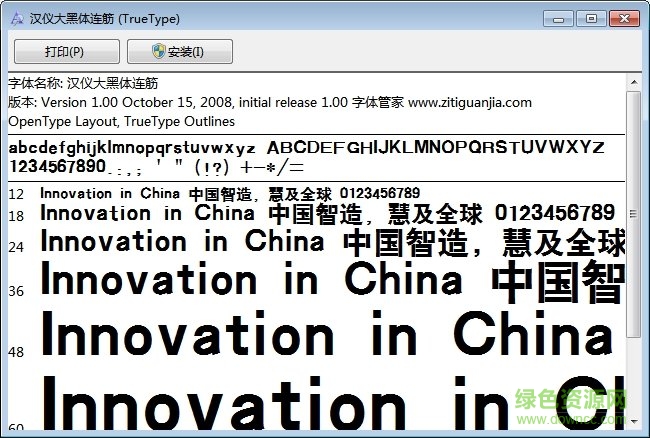
漢儀大黑體連筋字體是一款造型大氣恢弘、字跡清晰正直,給人十分醒目嚴(yán)肅的藝術(shù)體驗(yàn),用于正規(guī)條文、重要事情公告等標(biāo)準(zhǔn)文件上使用效果特別好,歡迎大家來綠色資源網(wǎng)下載收藏!
漢儀大黑連筋字體字形方正,筆畫橫平豎,直角分明,結(jié)構(gòu)嚴(yán)謹(jǐn),整齊均勻,整體風(fēng)格十分穩(wěn)重,常用作印刷中穩(wěn)重、醒目的標(biāo)題字。
漢儀大黑連筋體樸素大方、結(jié)構(gòu)嚴(yán)謹(jǐn),非常引人注目,一筆一劃都很正規(guī),顯示出做人端正一樣,非常適合廣告設(shè)計(jì)、平面設(shè)計(jì)、印刷包裝、正文標(biāo)題等人員使用。